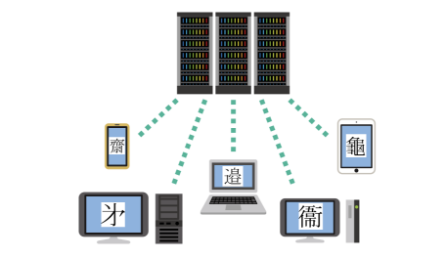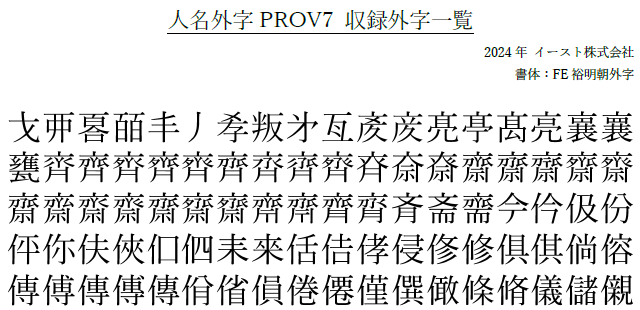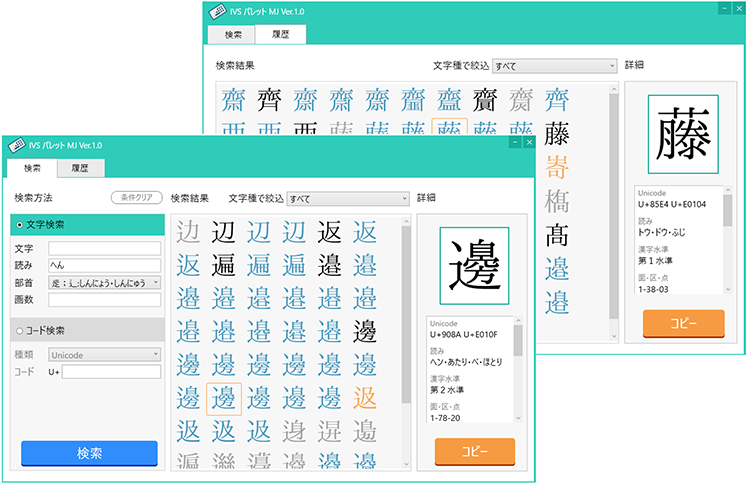
人名外字1500V7・PROV7シリーズ
60,000ユーザー突破!イーストが長年、外字作成サービスにて蓄積してきたノウハウをもとに使用頻度の高い人名用漢字を収録した外字フォント製品です。インストールするだけで、Officeはもちろん、各種業務アプリでもすぐにたくさんの外字が使えます。
人名外字1500V7
人名でよく使われる漢字(異体字、俗字等)を外字として合計1470文字搭載、学校現場の校務や企業の顧客サービス必携です。
人名外字PROV7
人名外字1500に漢字98文字と葬祭で使われる「変体かな」を278文字加えた計1816文字搭載。各種サービス業、冠婚葬祭などのプロの現場で活躍。
該当する外字を探すのが大変!
- 読みはもちろん、部首や部品でも検索が可能。
外字の入力作業は、検索が難しいものです。人名外字シリーズは、読みでの変換ももちろん、外字検索ツールを使えば部首や部品などでも検索が可能。似たような外字でも簡単に検索することができます。
人名外字シリーズ3つの特長
豊富な外字バリエーション
渡辺の「邊」「邉」、斉藤の「斎」「齋」など、細かい違いの異体字が多い文字は重点的に網羅しています。
読みで簡単入力
読みで入力できる、MS-IME・ATOK対応の変換辞書付属。通常の文字と同じように簡単・自然に入力できます。
検索ツールで簡単検索
付属の外字検索ツールを使えば、読み、部首、部品など様々な検索方法が可能。拡大して細かい部分の比較もできます。
収録外字一覧
人名外字1500V7
通常のパソコンの書体で表示できない、人名用の漢字(異体字、俗字等)を、外字として合計1470文字搭載しています。
人名外字PROV7
人名外字1500の外字に、更に漢字を98文字と葬祭でよく使われる「変体かな」を278文字を追加、計1816文字を搭載。
教育委員会
長年、様々な教育委員会様でお使い頂いている人名外字シリーズ。校務システム、学籍管理や賞状印刷などで、お名前を正確に表示することが可能になります。
葬祭業
人名外字PROシリーズには、古くから使われている変体仮名を収録。葬祭の現場における看板や供花・供物札、デジタルサイネージでも正しいお名前で表示が可能です。
ブライダル
デジタルサイネージなどの新郎新婦名の表示を始め、参列者の方や席次表などのお名前を正しい漢字で表示・印刷することでおもてなしの心が表せます。